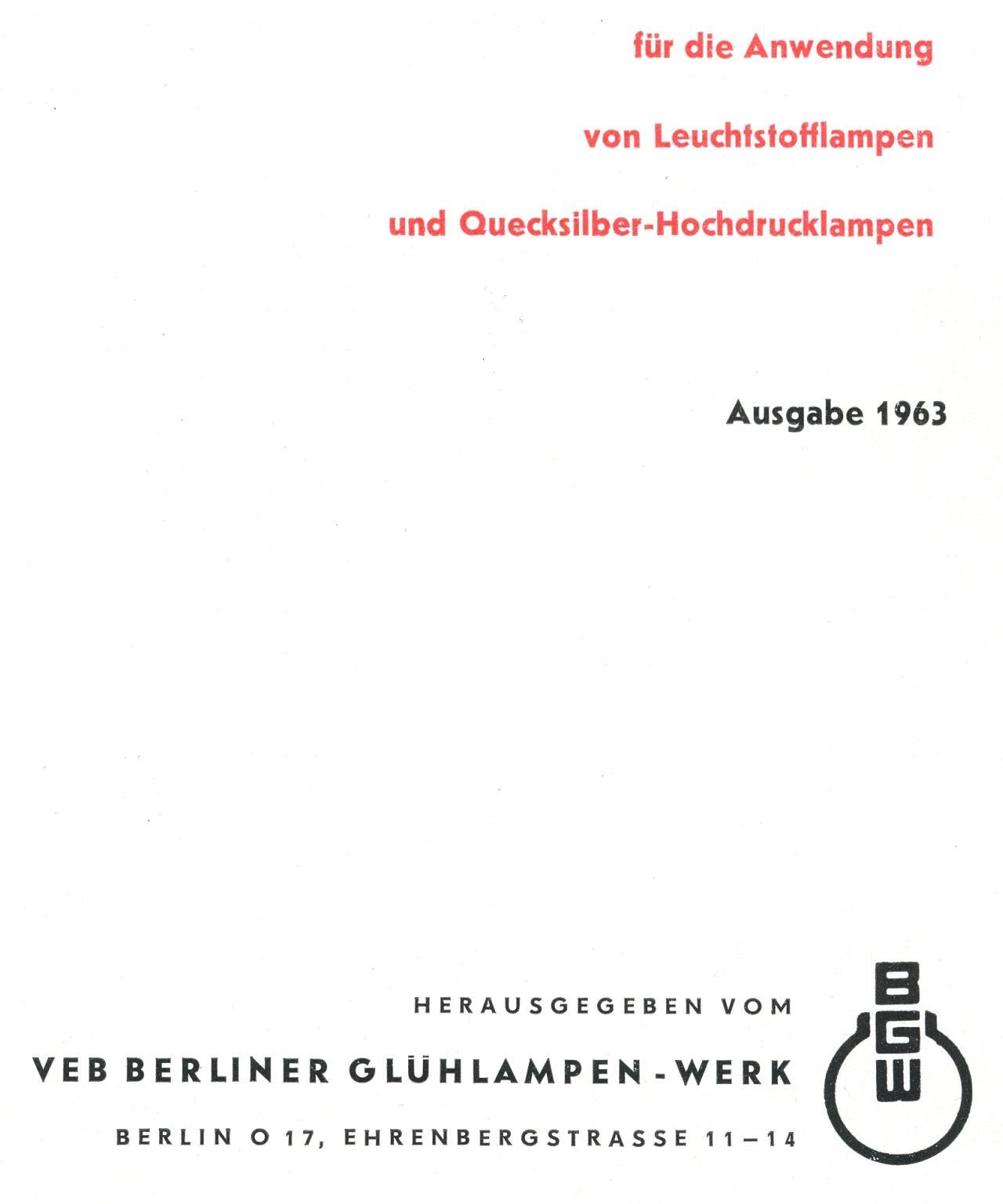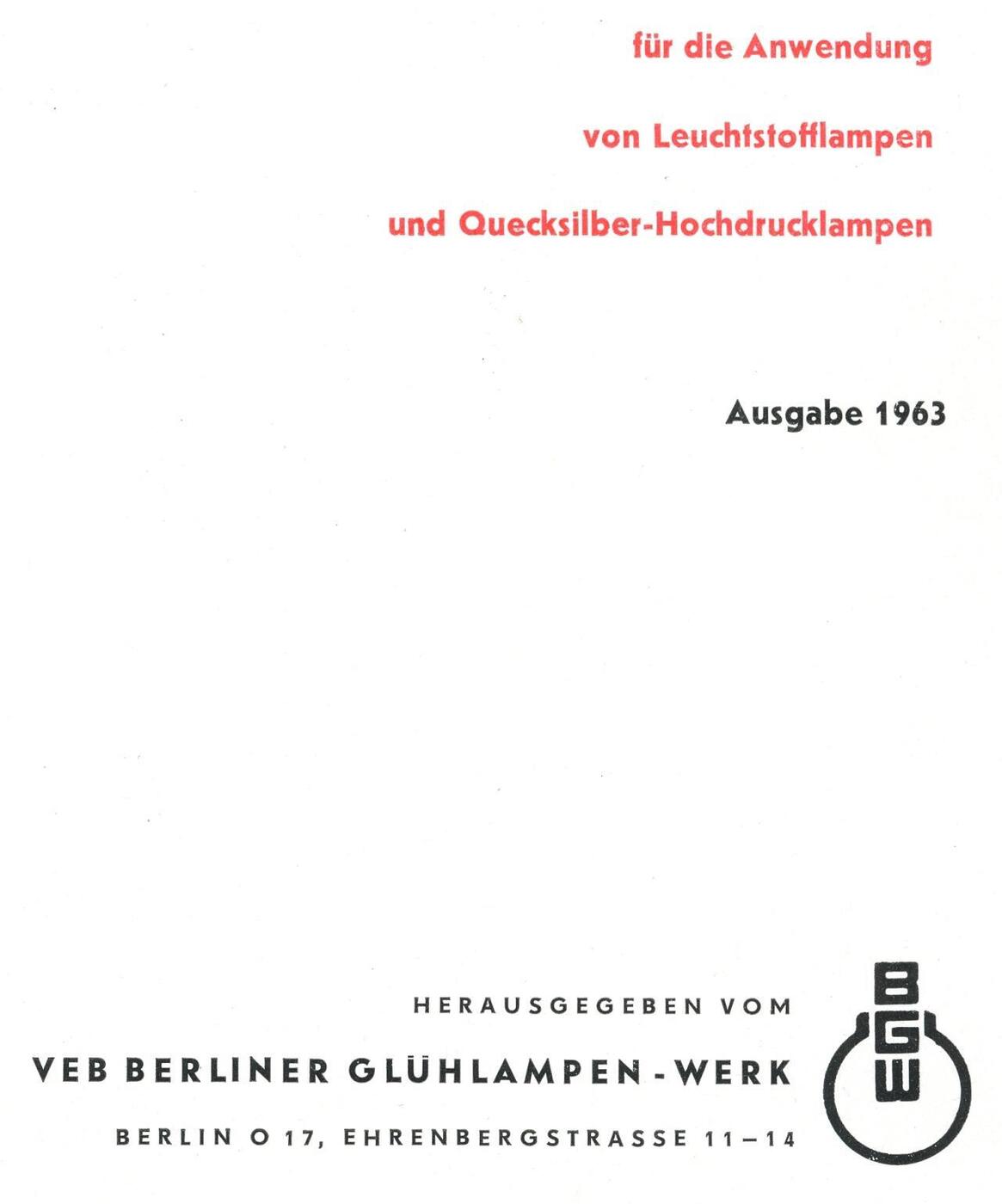
Druckschrift des VEB Berliner Glühlampenwerk von 1963; Frage zur Schriftart
meine Anfrage bezieht sich auf die Innentitelseite einer Druckschrift des VEB Berliner Glühlampenwerk aus dem Jahr 1963.
Orientiert habe ich mich als völliger Laie an dem kleinen Buchstaben "a" und es bereits mit diversen Schriftarten aus DDR-Zeiten verglichen. Eine völlige Übereinstimmung habe ich aber nicht gefunden, deshalb wende ich mich nun mit meiner Frage an das Forum. Was für eine Schriftart ist das ?